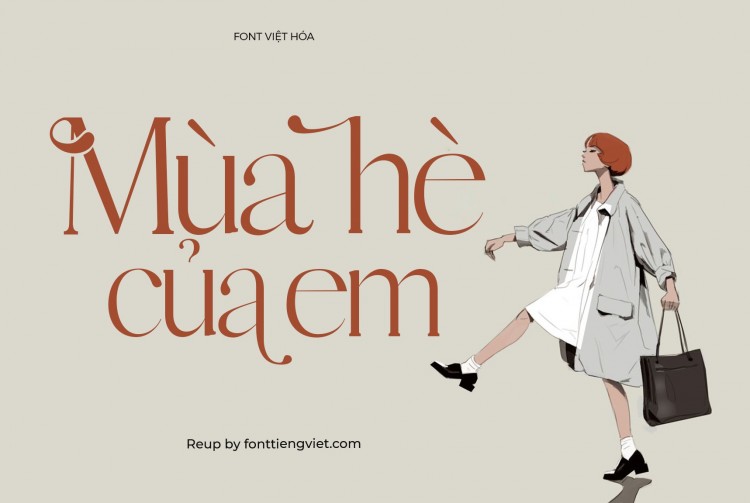
Font Việt hóa TF Moncheur Havens – Nhiều Glyphs đẹp
Tên font: Font Việt hóa TF Moncheur Havens – Nhiều Glyphs đẹp
Tác giả: FontVietHoa.Org
Font Việt hóa TF Moncheur Havens được thiết kế tinh tế, Font có nhiều Glyphs đẹp
Bạn sẽ cảm thấy thích thú với font chữ này. Nó quá tuyệt vời để sử dụng trong các thiết kế cần sang trọng quý phái